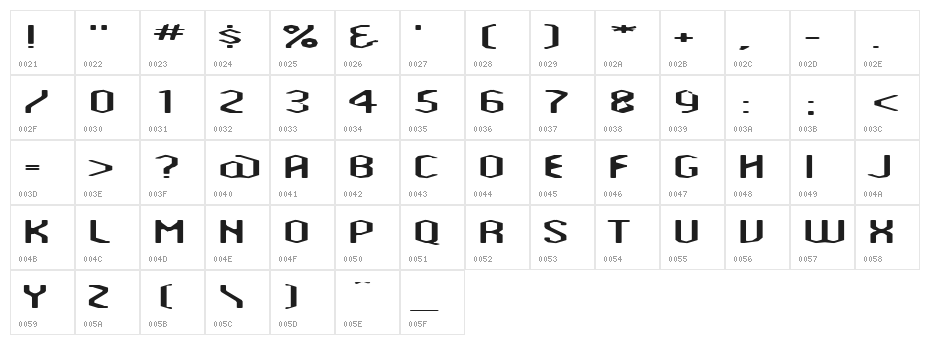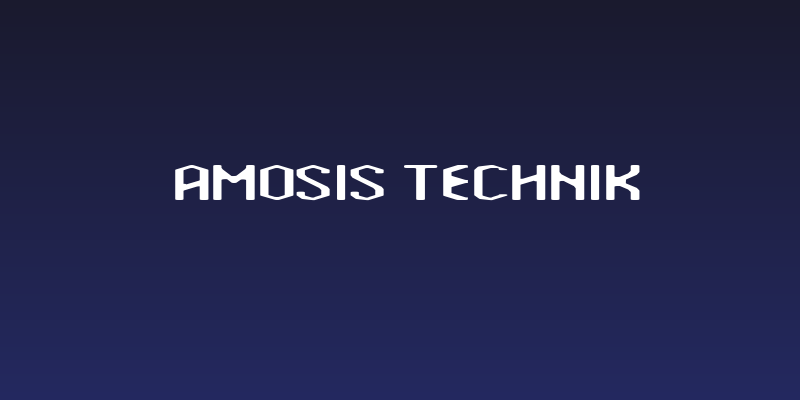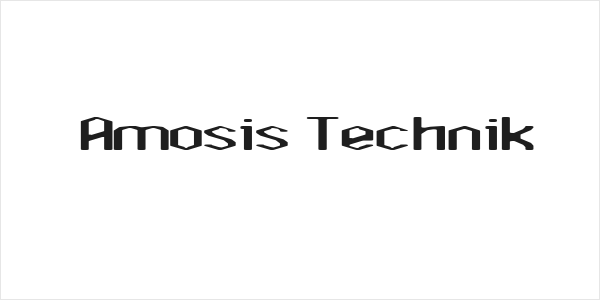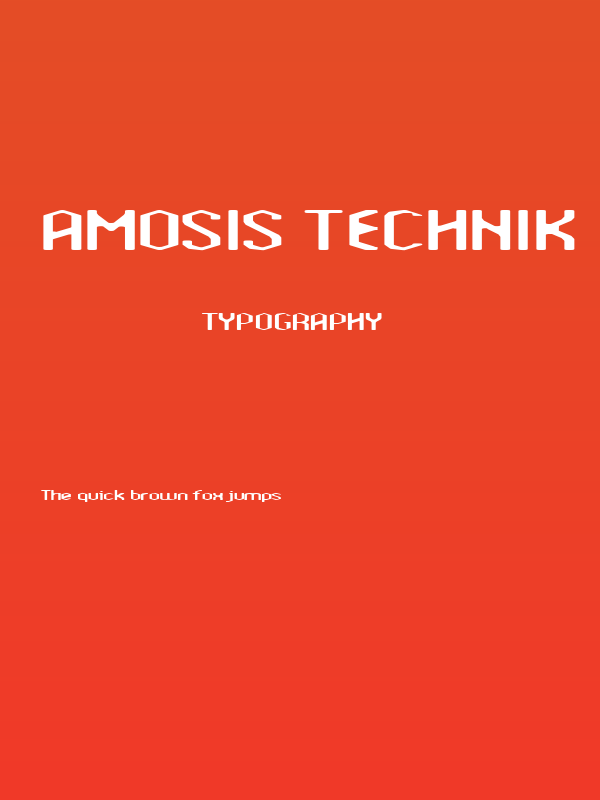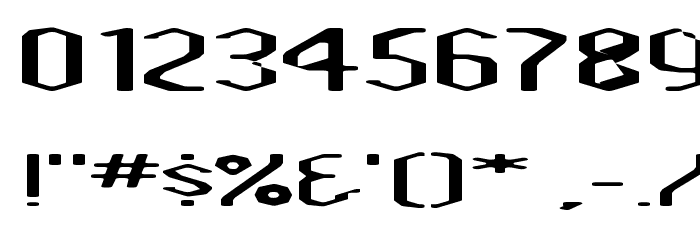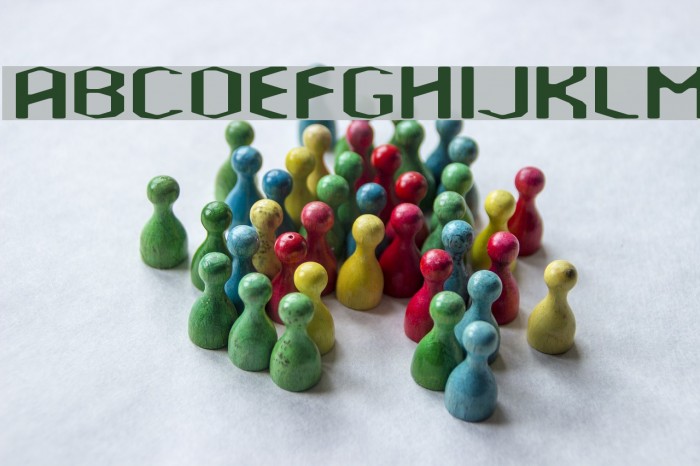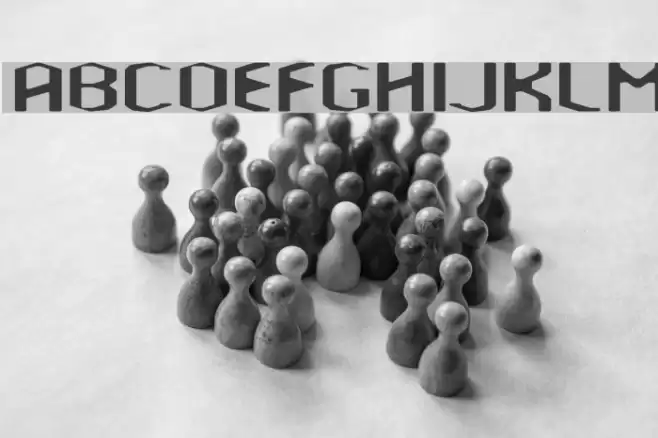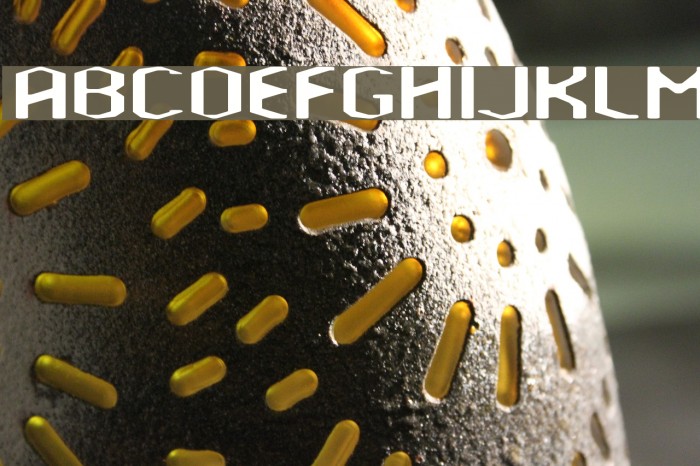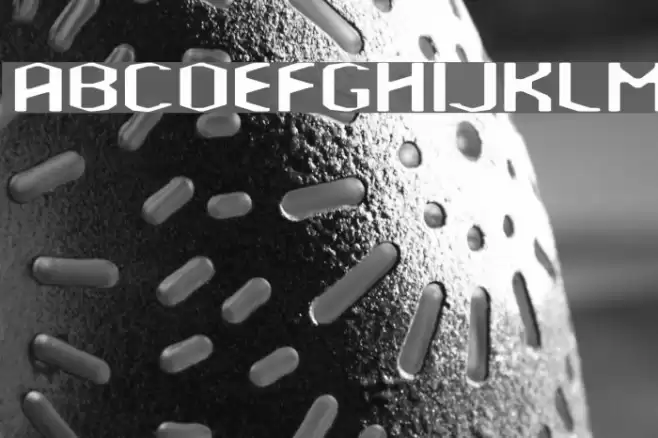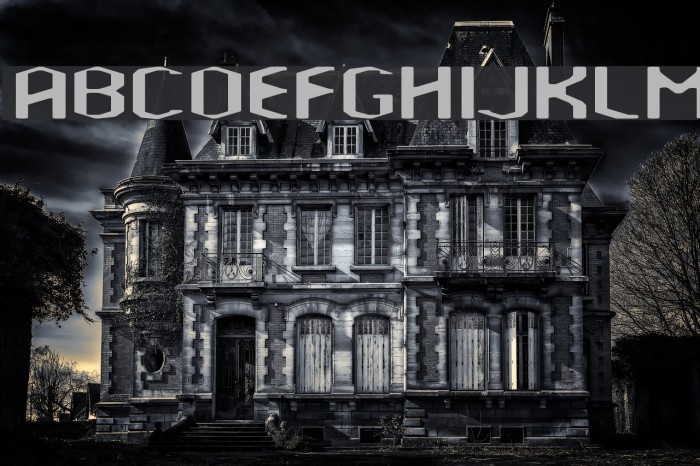
Amosis Technik Font
| Anwendungsfall | Logos, Headlines, Posters |
| Vorgeschlagene Projekte | Ideal for technology branding, sci-fi themed designs, video game interfaces, and modern advertising. |